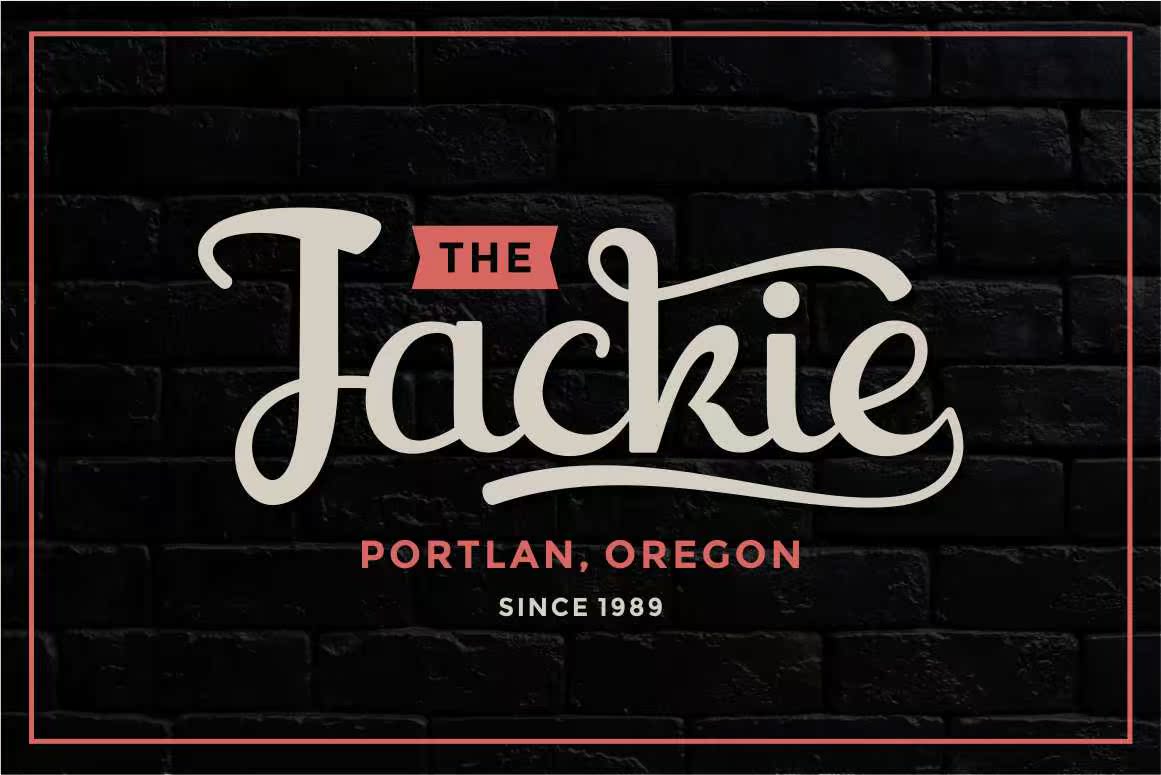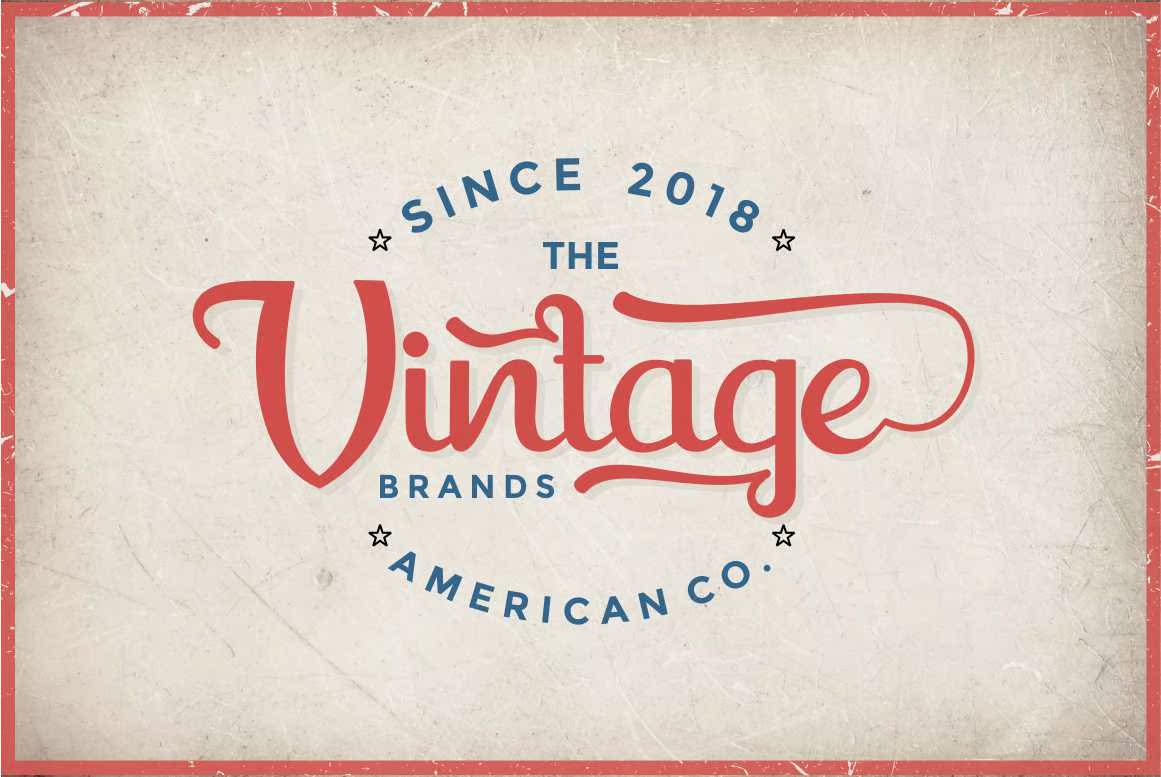
ShaquillaisModernClassicStyleFont。它包含一整套大小写字母、标点符号、数字和多语言支持。我希望这能让你从工作中获得灵感。理想的日志、手写引号、产品包装、标题、海报、商品、社交媒体、标签、,品牌和问候卡。ShaquillaisModernClassicStyleFont。它包含一整套大小写字母、标点符号、数字和多语言支持。我希望这能让你从工作中获得灵感。理想的日志、手写引号、产品包装、标题标题、海报、商品、社交媒体、标签、品牌和问候卡。